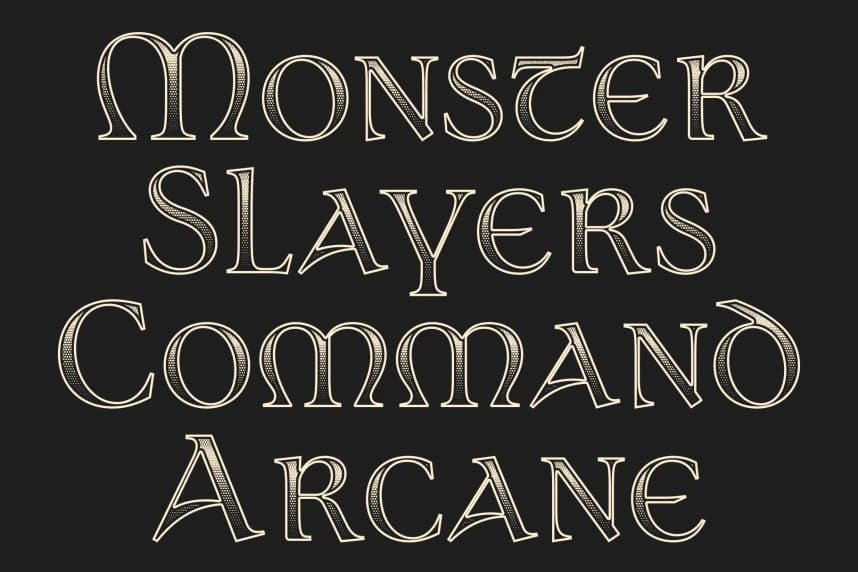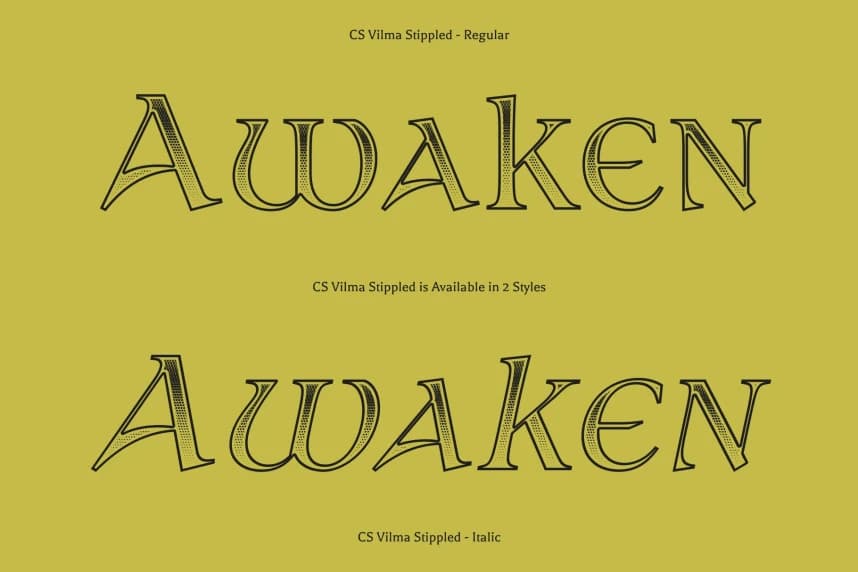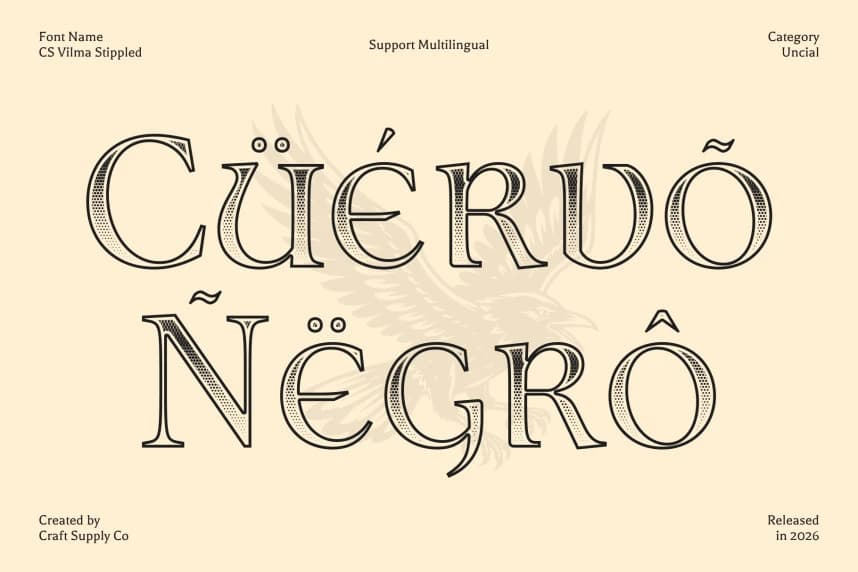
CS Vilma Stippled Yazı Tipi
CS Vilma Stippled Font – Uncial Font ile Zarif Tarihî Doku, Klasik Uncial Tarzı ve Stippled Depth. Bu, Orta Çağ'ın zarif el yazısından esinlenen klasik bir uncial serif gösterim yazı tipidir.
CS Vilma Stippled Font – Zarif Tarihi Dokuya Sahip Uncial Yazı Tipi, Benekli Derinlikli Klasik Uncial Stili. Bu, Orta Çağ Dönemi Zarif El Yazısından Esinlenen Klasik Bir Uncial serif Gösterim Yazı Tipidir.